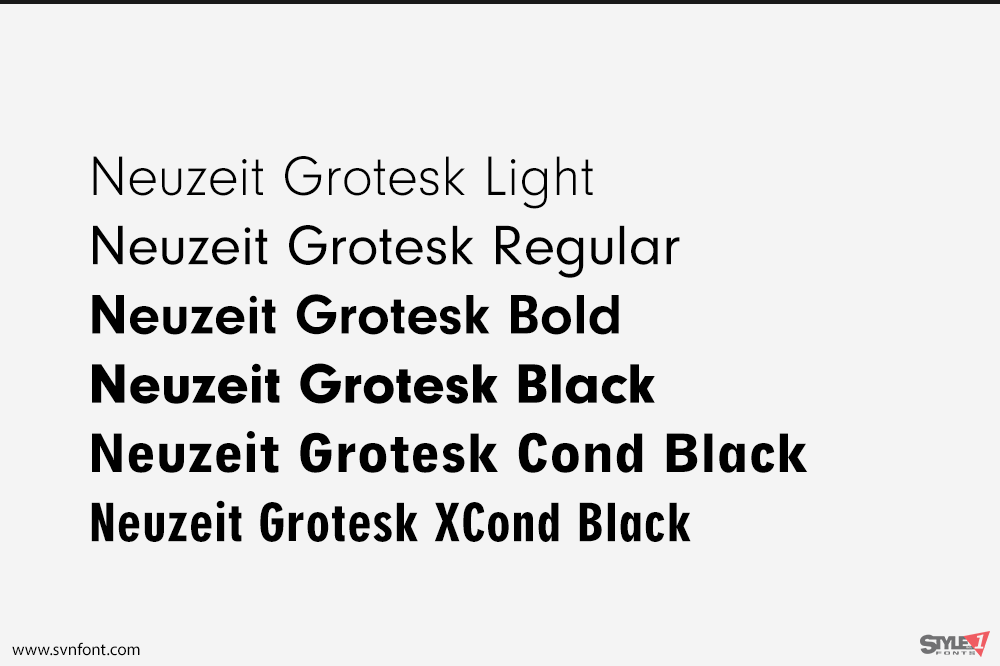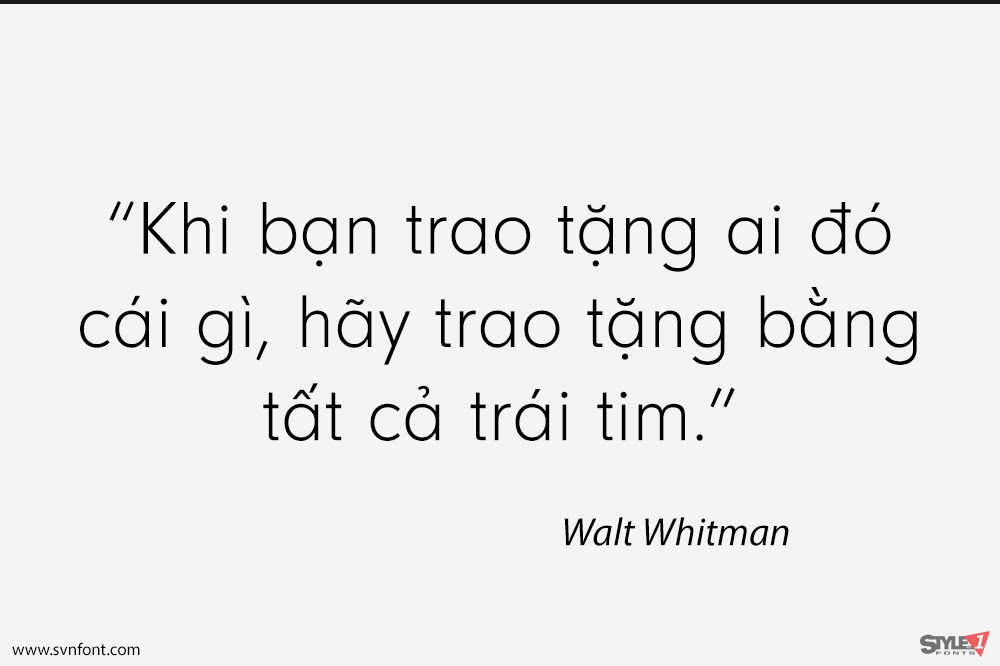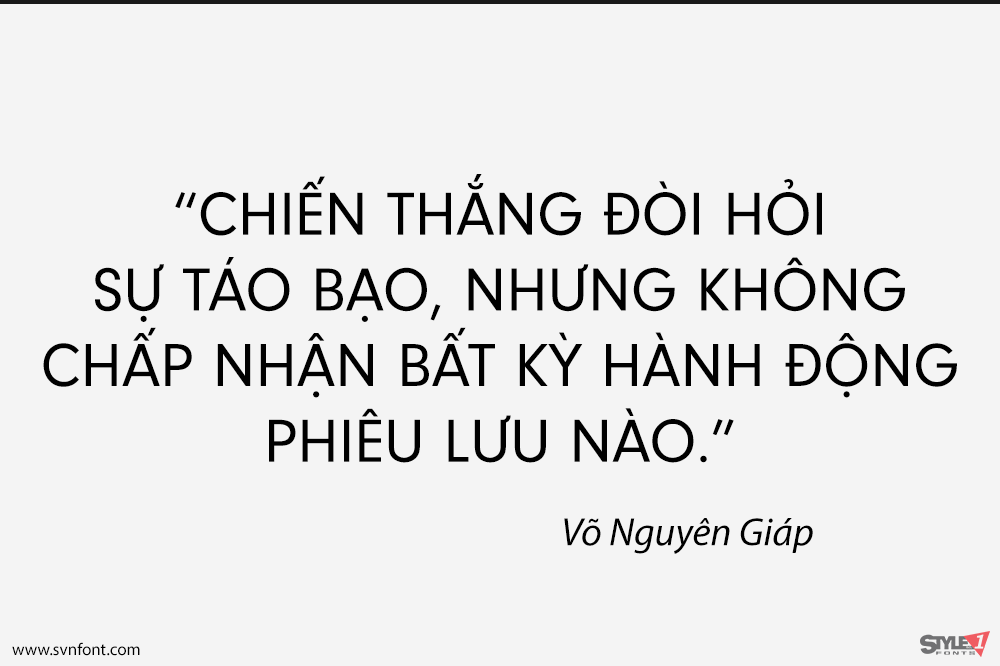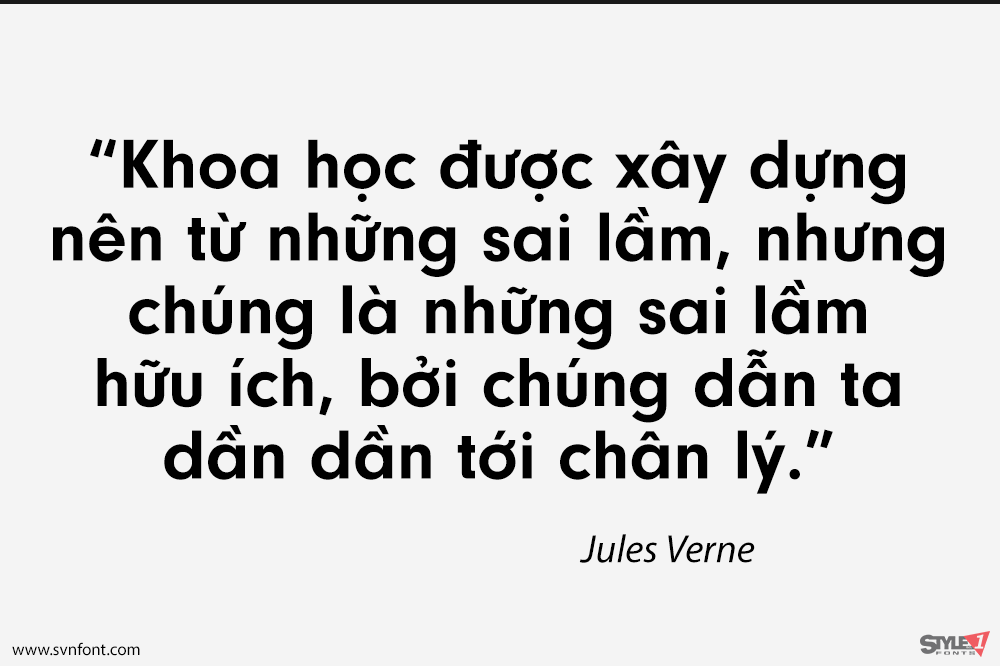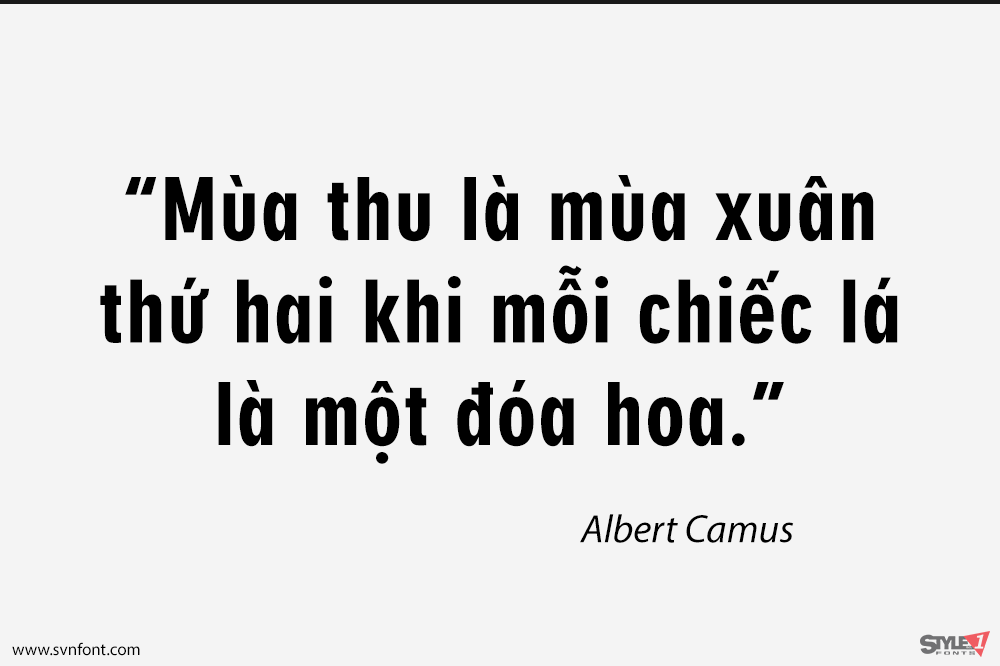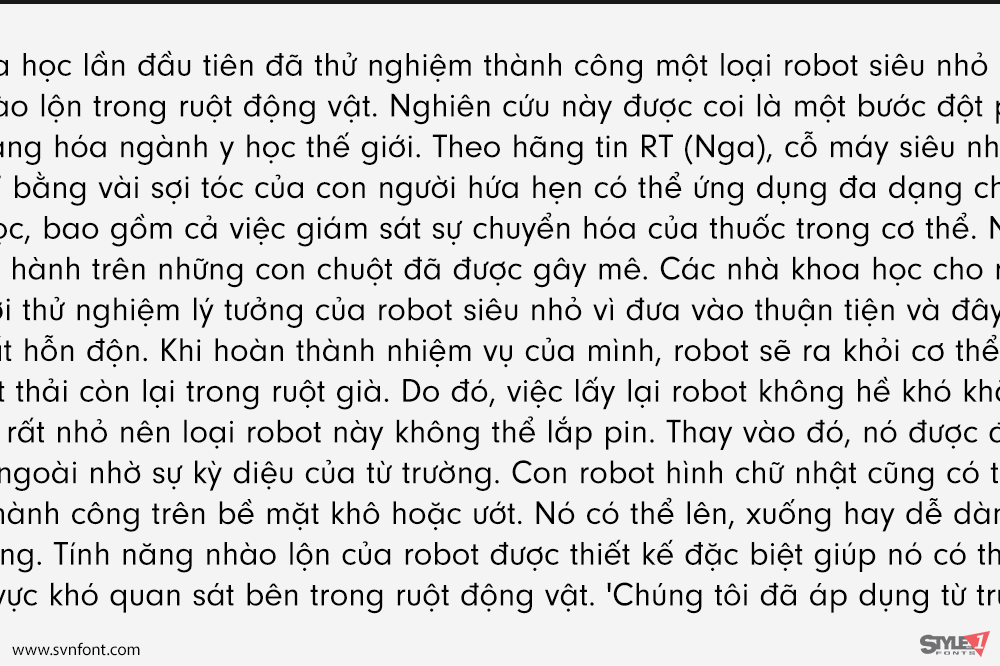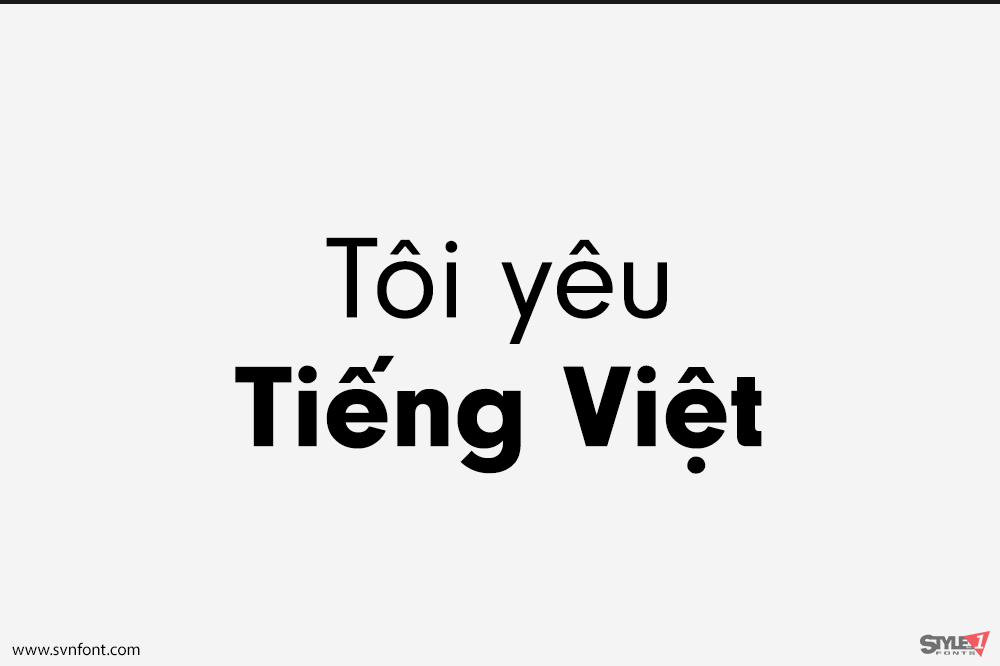
Neuzeit Grotesk là một bộ font chữ không chân gồm 6 fonts được thiết kế bởi Wilhelm C. Pischner. Với thiết kế hiện đại và tươi mới, font chữ phù hợp cho nhiều thiết kế khác nhau như: logo, bảng hiệu, bao bì nhãn mác sản phẩm, slide thuyết trình…
Nhà thiết kế: Wilhelm Pischner
Nhà phát hành: URW Type Foundry